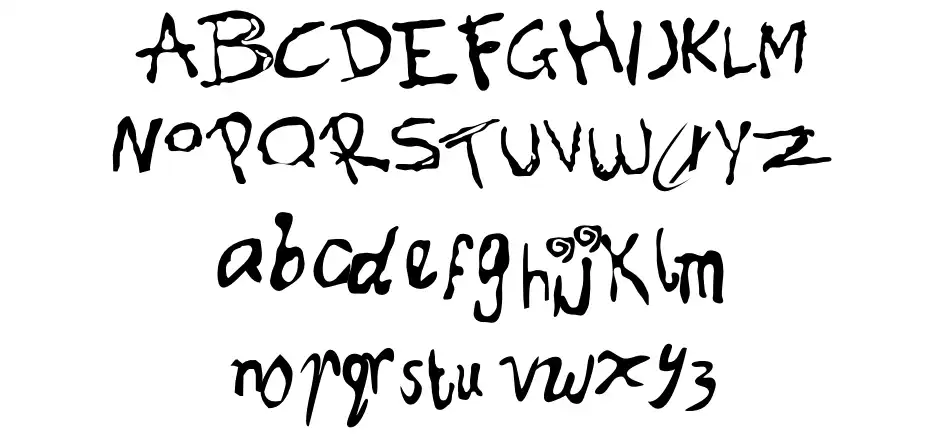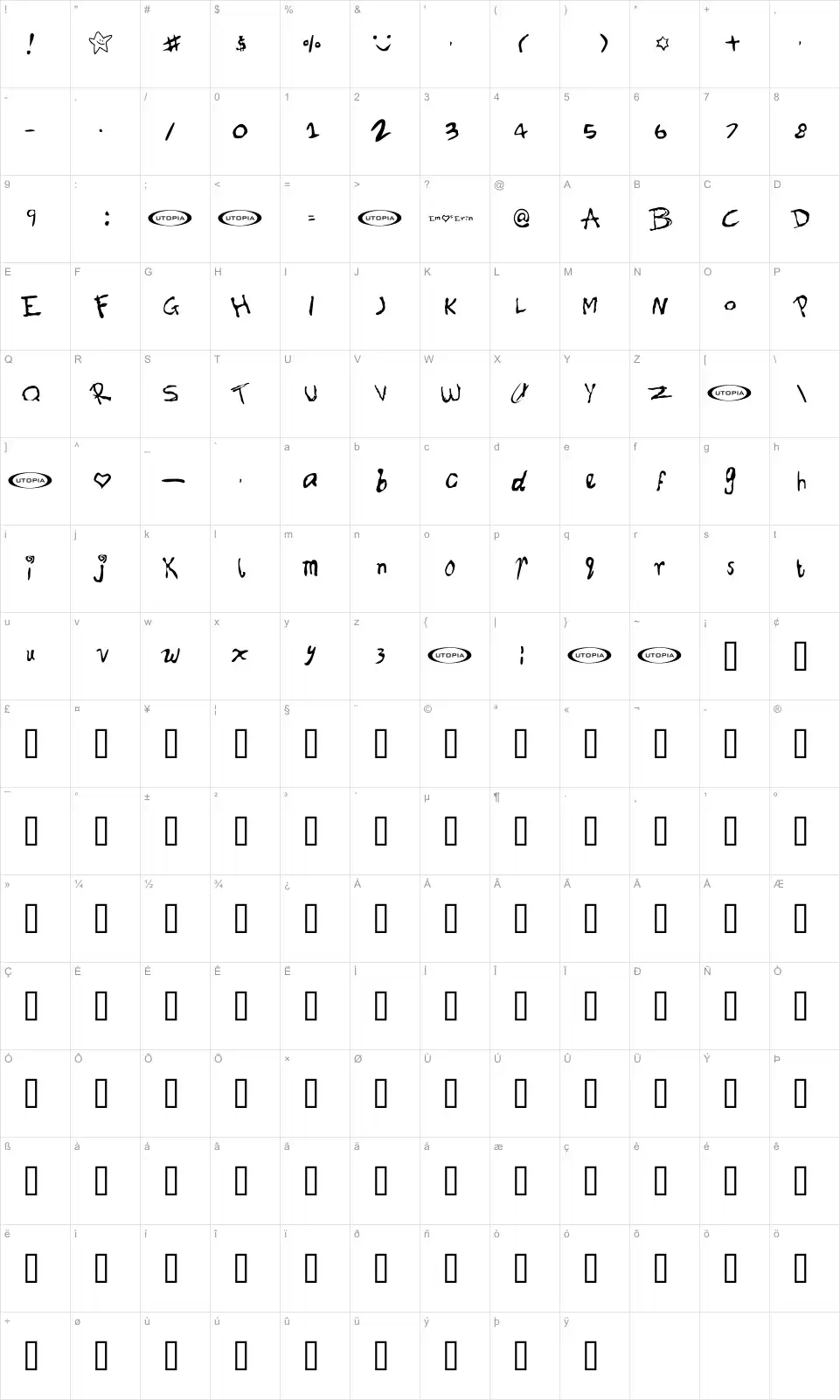
Font for Erin – Download Grátis
A fonte ‘Font for Erin’, criada pela Utopia, é perfeitamente adequada para aqueles que buscam um efeito sofisticado e elegante em seu projeto de design. Se você está à procura desta fonte, é hora de fazê-la sua, seja para personalizar seu texto ou para dar um toque especial ao seu design. A Utopia oferece a opção de download da font ‘Font for Erin’ em formato TTF, que é popular e compatível em uma variedade de plataformas. Esta font se enquadra na categoria de script e é uma ótima escolha para designers que procuram algo versátil e versátil para projetos diversos. Sua adição em 12 de julho de 2022, junto com 1568 downloads, demonstra sua popularidade e qualidade. Com um tamanho de 34 KB, é uma opção conveniente e rápida para seu design. Se você deseja explorar ainda mais essa fonte, o próprio designer, Dale Harris, mantém um site onde você pode acessar e conhecer mais detalhes sobre sua obra.